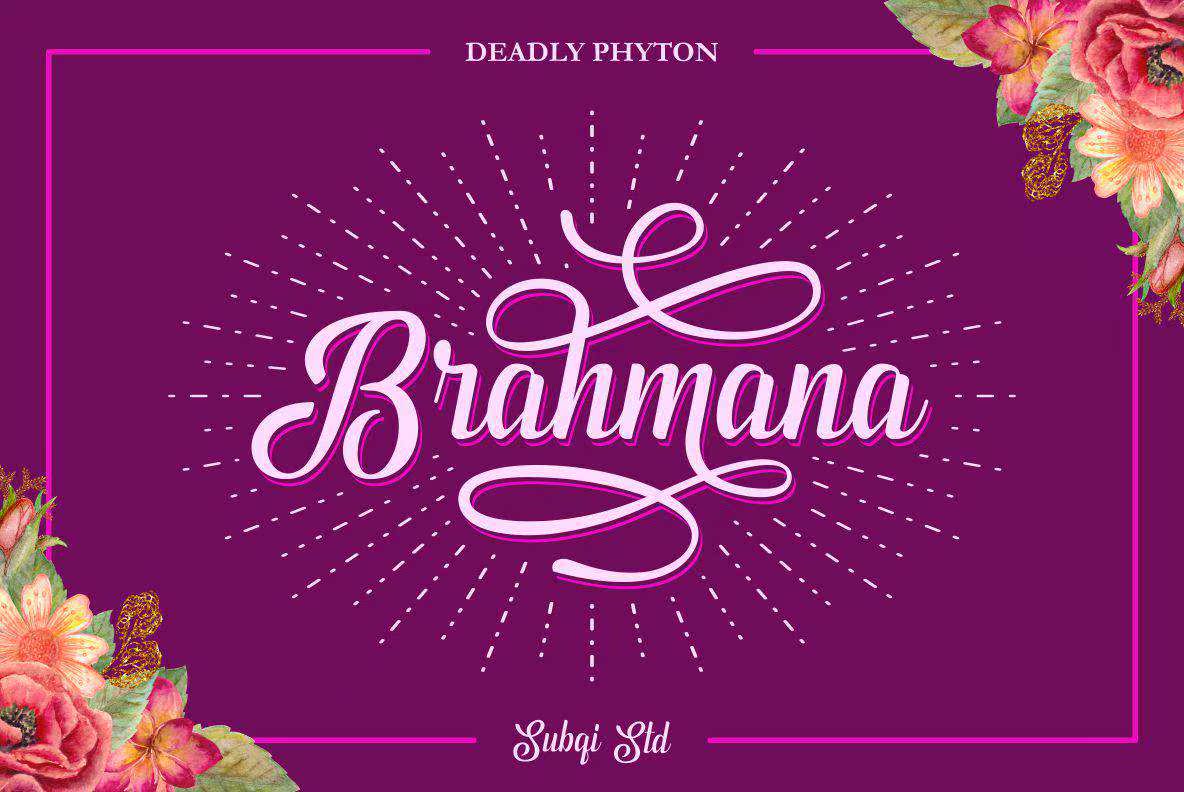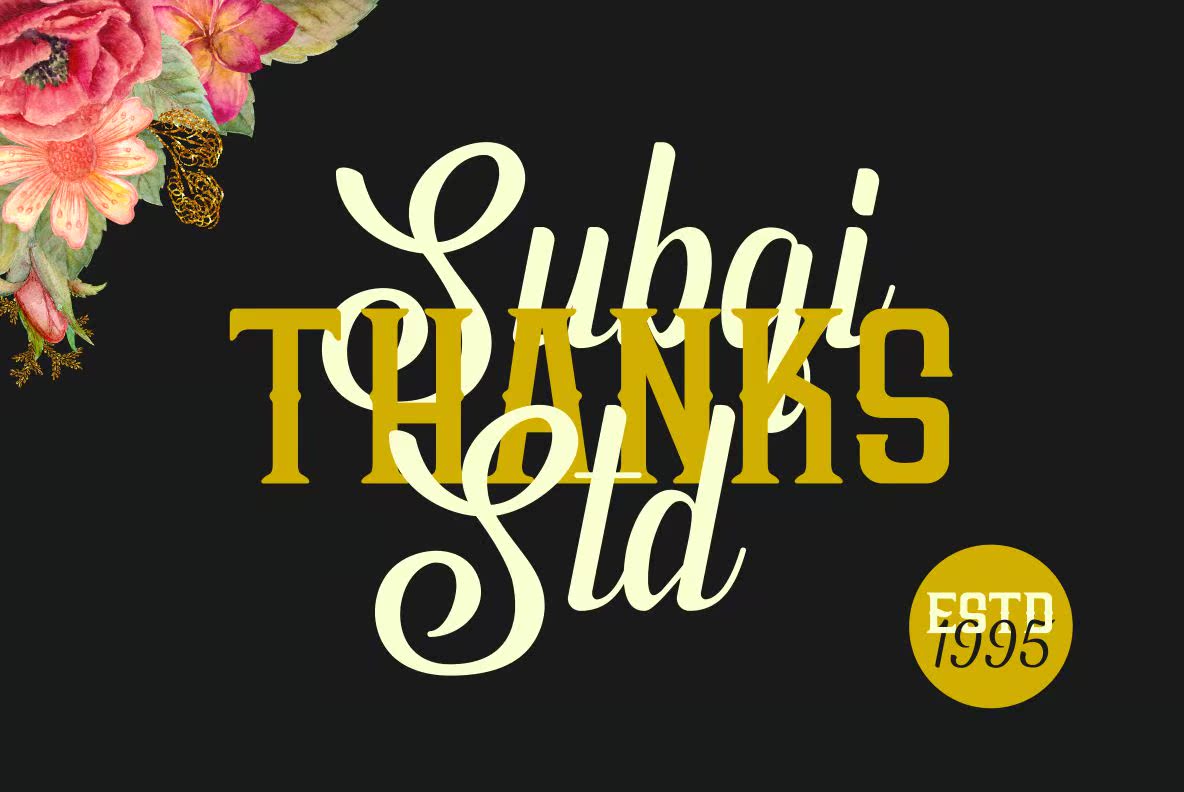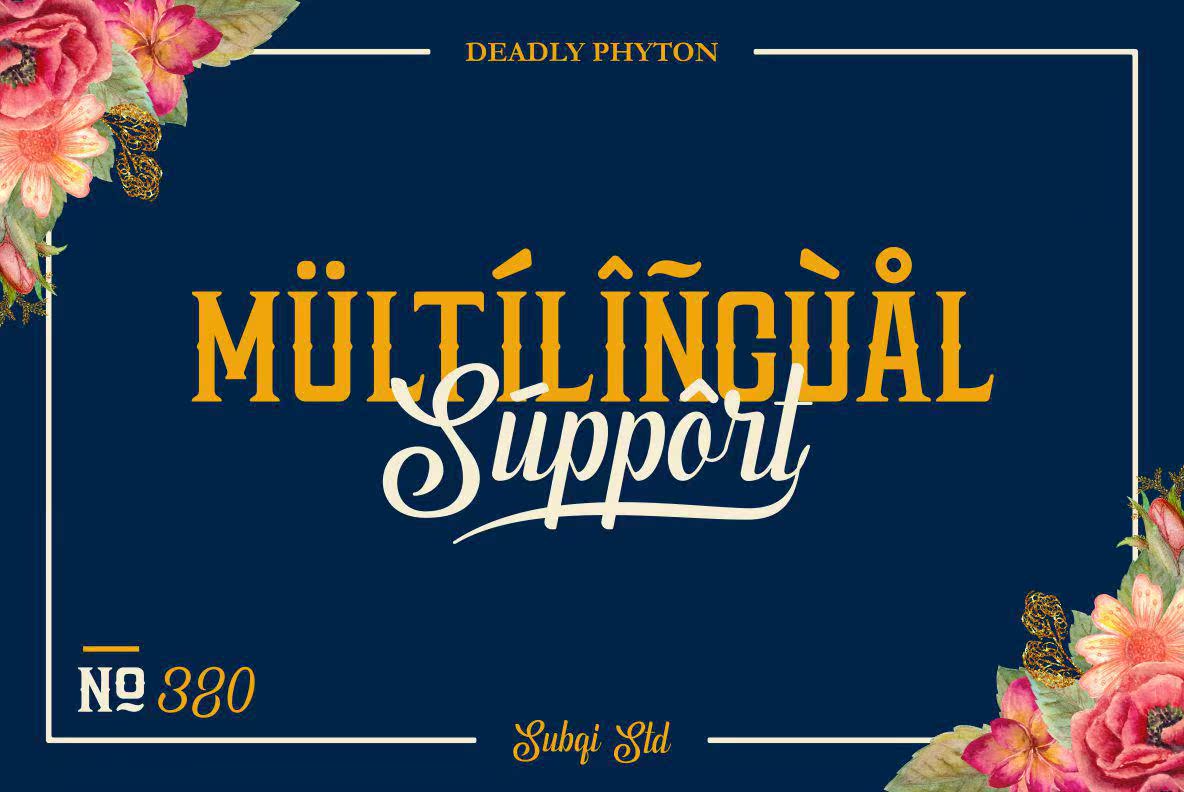
自豪地展示我们的新产品。致命的植物人!AlligraphyScript和Serif.Workwell在维护和现代设计方面的完美结合,让您可以查看更多预览图片示例。自豪地展示新产品。致命的植物mbo!AlligraphyScript和Serif.Workwell之间的有效组合,无论是维护还是现代设计,您都可以查看网页预览示例。